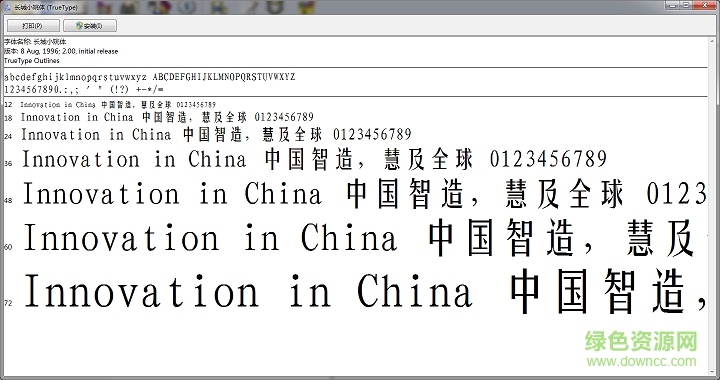
gyao00m(長城小姚體)字體是一款雋秀修長的長城字體,筆畫簡(jiǎn)潔,線條干練,結(jié)構(gòu)工整規(guī)范,字形清秀漂亮,適合排各類文章標(biāo)題、廣告設(shè)計(jì)、包裝設(shè)計(jì)等!喜歡就來綠色資源網(wǎng)下載吧!
gyao00m字體,結(jié)構(gòu)狹長,字間距較大,排印清晰,整齊劃一,適用于書籍、報(bào)刊、雜志的標(biāo)題字。姚體在宋體的基本骨架上融合了黑體和仿宋體的特點(diǎn),采取更為簡(jiǎn)潔概括的筆畫形態(tài),整體字型清秀瘦長、端莊正氣,呈現(xiàn)出非常鮮明的“美術(shù)字”風(fēng)格。